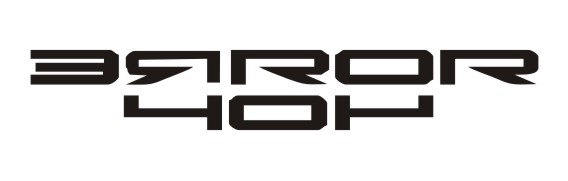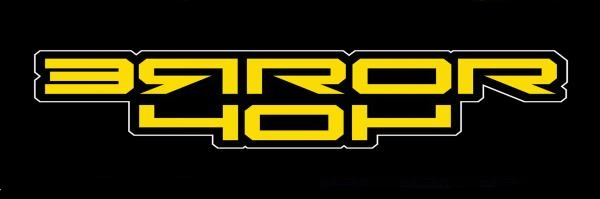
Suche bestimmte Schriftart
ich finde diesen schrift art nicht kann mir das vieleicht jemand hier posten bitte
oder vieleicht macht sich wer die arbeit und schreibt das hier rein das ich es rauskopieren kann
ERROR 404 nur in der schrift wie es in dem foto ist bitte
hab heute schon den ganzen tag probiert das zu bekommen kann mir einfach nicht weiterhelfen desweg bin ich hier ich flehe euch an bitte helft mir
Schon mal daran gedacht, daß das gar keine Schrift sein muß sondern einfach eine Grafik ist....!? :o
ja is ja wieder ein bild
brauch das als text
komm nicht kar irgend wie macht mich das ding
habs grad wieder die ganze zeit probiert
ich checkt das mit der spielgel schrift nicht
Wenn Du immer noch dem Irrglauben unterliegst, dass es sich dabei um eine Schriftart handelt, dann kann Dir niemand helfen!
hab doch die schrift gefunden ich weis das es ein bild ist
nun hab ich das problem das ich das r nicht drehen kann und das e vom error
Vielleicht hab ich mich nicht ganz klar ausgedrückt.
Es mag wohl sein, dass Du eine Schriftart findest die ähnlich oder exakt so aussieht. Der Schriftzug als solches - mit den teilweise gespiegelten Buchstaben - ist jedoch in einem Grafikprogramm umgesetzt worden.
Du wirst den Schriftzug - so wie wir ihn alle sehen - in keinem textorientierten Programm erstellen und/oder bearbeiten können.
EDIT: Auch wieder nicht ganz richtig. Ich kann aus den vorliegenden grafischen Teilen eine Schriftart machen, ...